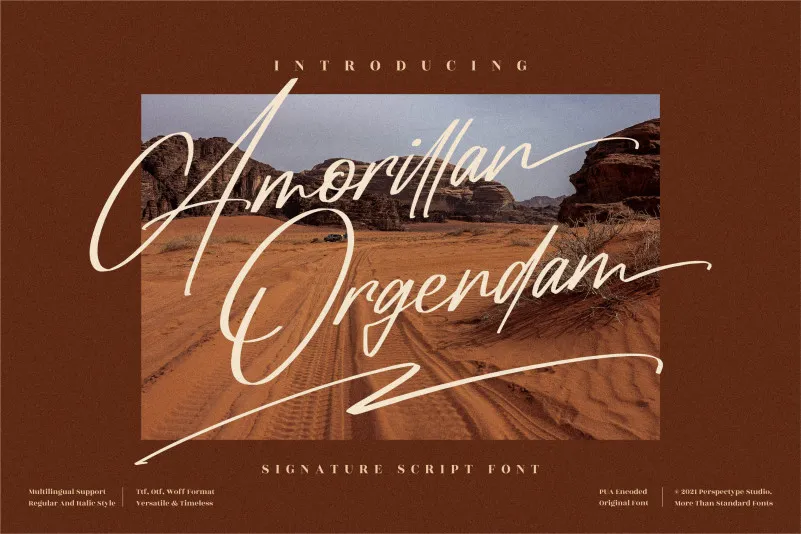
Amorillan Orgendam Font – Fonte Grátis
Amorillan Orgendam Font
A ‘Amorillan Orgendam Font’ é uma elegante fonte escrita à mão que combina delicadeza com beleza sofisticada. Oferecida sob a categoria de fuentes escritas à mão, esta fonte de letra fina e delicada é especialmente perfeita para quem busca um estilo romântico na sua próxima criação gráfica. O fato de ser PUA encoded significa que você pode facilmente acessar todos os gílios e swashes da fonte. Perfeito para criar designs memoráveis, esta fonta invadiu o coração dos amantes do bom design com seu estilo fashionista único. Descubra o encanto dela e use-a para dar um toque romântico em seus projetos digitais ou impressos.